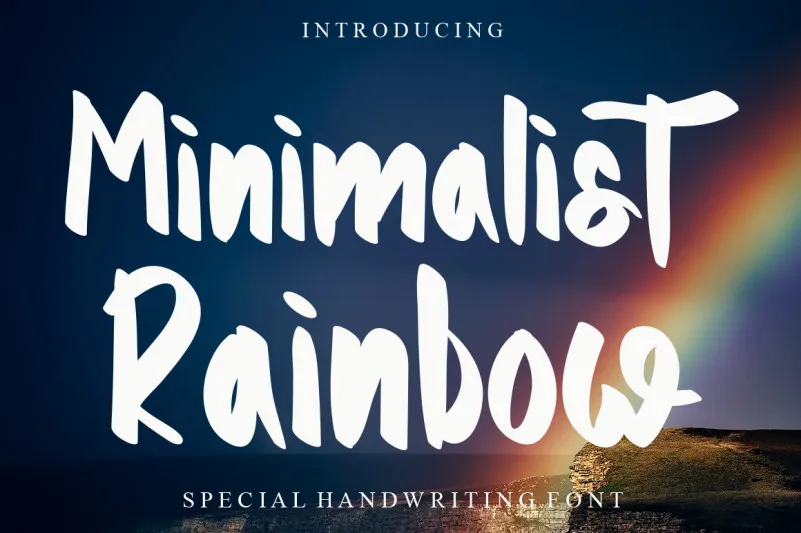
Minimalist Rainbow Font – Download Grátis
Esta fonte é ideal para aqueles que buscam uma abordagem amigável e divertida para seus projetos digitais. Com sua aparência cuidadosamente escrita, a “Minimalist Rainbow Font” de LevinCreative oferece um toque moderno e trendy aos seus trabalhos. Sua linha limpa e elegante, característica da cunha, a torna uma escolha ideal para quem deseja dar um toque inovador e criativo às suas criações digitais. Seu design colorido e vibrante também contribui para criar uma atmosfera descontraída e animada nos seus projetos. Com “Minimalist Rainbow Font”, você pode transformar seu trabalho em algo realmente distinto, capaz de destacar-se no meio da multidão. Perfect para designers gráficos, web designers ou qualquer designer que deseje dar um toque alegre e único às suas criações digitais.